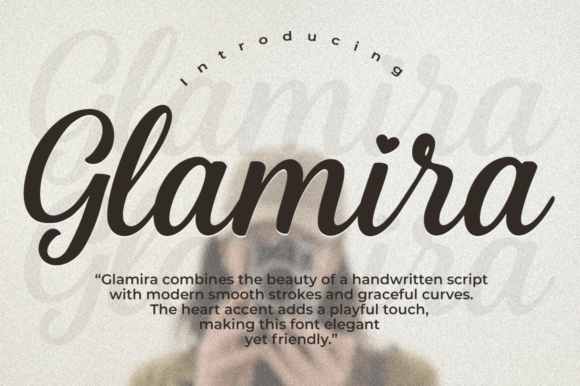
Glamira Script
Trouver les bons éléments de conception peut être un défi, mais Glamira Script propose une collection exceptionnelle qui rehausse instantanément votre travail.
Que vous créiez des produits POD (impression à la demande), des invitations de mariage ou des visuels pour les réseaux sociaux, Glamira Script est un choix idéal.